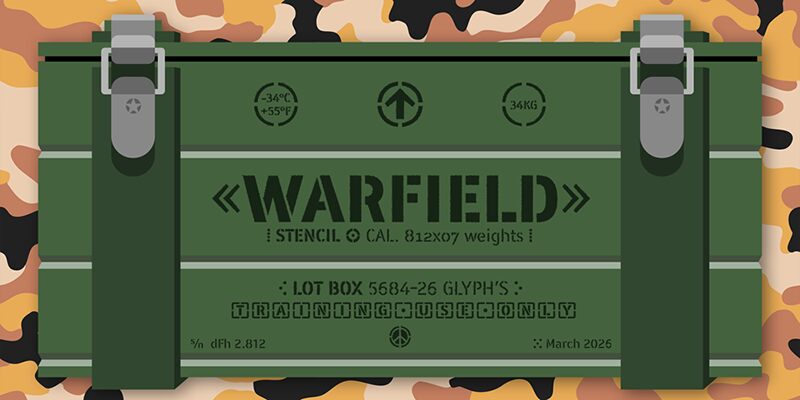
WARFIELD Regular
Warfield, entworfen von Fernando Haro von deFharo, ist eine kostenlose Military-Stencil-Display-Schrift mit einer scharfen, disziplinierten Ästhetik. Ihre hohen, schmalen Lettern, die präzisen Schnitte und die gleichmäßigen Zwischenräume wirken wie auf Metallkisten oder Fahrzeugpaneele gesprüht und verleihen Ihren Texten eine robuste, taktische Präsenz, ohne die Lesbarkeit zu beeinträchtigen. Die enge Laufweite und die strengen vertikalen Linien erzeugen ein Gefühl von Spannung und Dringlichkeit – ideal für alles, was mit Action, Konflikt oder Strategie zu tun hat.
Nutzen Sie Warfield für das Branding von Airsoft- oder Paintball-Teams, Game-Titel, Filmplakate, Verpackungen für taktische Ausrüstung, Event-Beschilderungen oder kraftvolle Sport-Grafiken, die diese kompromisslose, militärische Energie ausstrahlen sollen. Diese kostenlose Schriftart glänzt besonders bei großen Größen, wo die Stencil-Brüche klar zur Geltung kommen. Kombinieren Sie sie für den Fließtext mit einer klaren geometrischen serifenlosen Schrift, um Ihre Layouts stark und leserlich zu halten.
WARFIELD is, by definition, a stencil typeface, drawing from its military and industrial heritage, but shedding any aggressiveness to embrace absolute legibility.
It is a contemporary sans-serif that is not only read but also felt, proudly displaying the breaks, bridges, and interruptions that define it, giving it a straight and solemn bearing.
From the ethereal subtlety of Light to the resounding authority of Black, Warfield offers seven weights designed to withstand any creative battle.
It is a contemporary sans-serif that is not only read but also felt, proudly displaying the breaks, bridges, and interruptions that define it, giving it a straight and solemn bearing.
From the ethereal subtlety of Light to the resounding authority of Black, Warfield offers seven weights designed to withstand any creative battle.